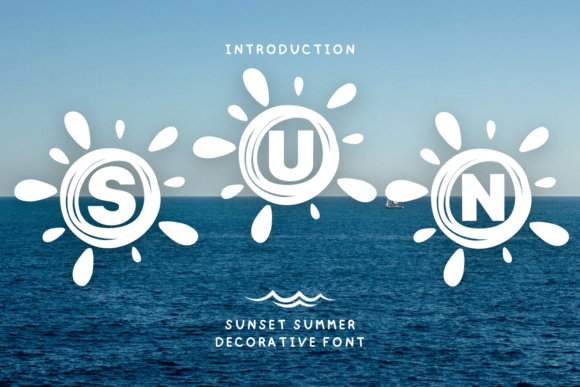
Sunset Summer
Việc tìm kiếm các thành phần thiết kế phù hợp có thể là một thách thức, nhưng Sunset Summer cung cấp một bộ sưu tập đặc biệt giúp nâng tầm công việc của bạn ngay lập tức.
Được chế tác với độ chính xác cao, Sunset Summer cung cấp các vector sạch, kiểu chữ mượt mà và giấy phép thương mại để bạn yên tâm.